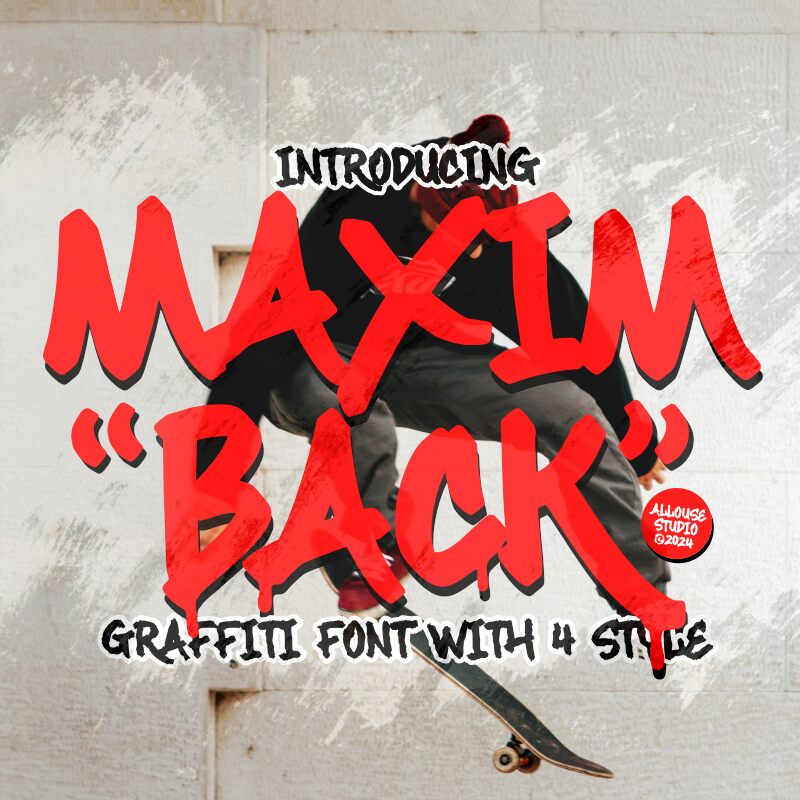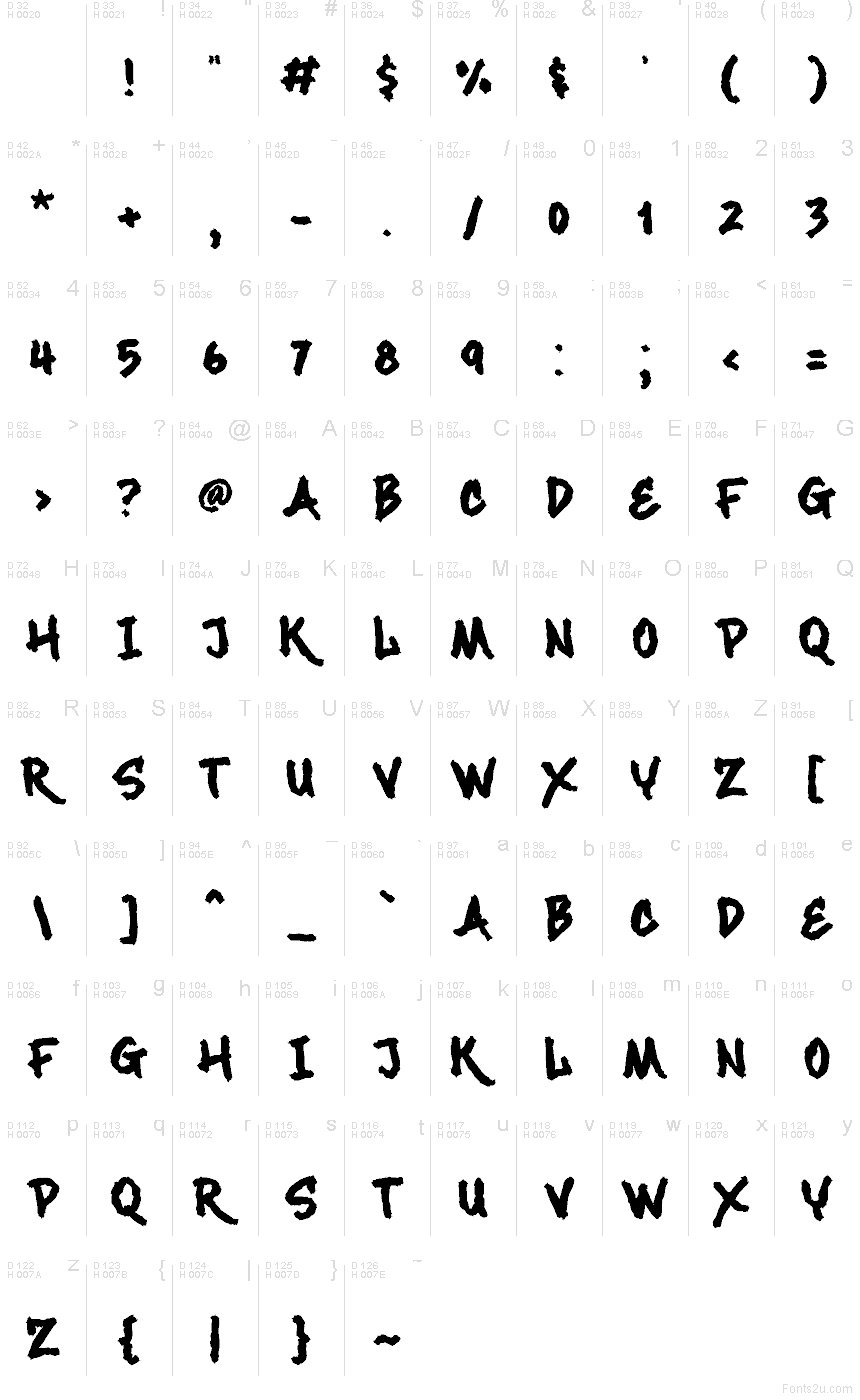
خط Maximback Distressed من Allouse.Studio هو خط مجاني بأسلوب الجرافيتي، يتميز بضربات قوية ومشبعة بالطلاء تبدو وكأنها رُسمت بسرعة على الجدار. تمنح الحواف الخشنة والنهايات الحادة الحروف ملمساً خاماً وجريئاً، مما يجعله يبدو أقرب إلى "تاغ" الشوارع اليدوي منه إلى خط الفرشاة المصقول.
هذا المظهر الخام مثالي لتصاميم ملابس الشارع (ستريت وير)، وملصقات الموسيقى، وعلامات التزلج التجارية، ونشرات الفعاليات، وعناوين التواصل الاجتماعي حيث تبدو الخطوط النظيفة مملة جداً. إنه خيار ممتاز للعناوين القصيرة والعبارات المؤثرة، خاصة عندما تريد أن تكون خشونة الفرشاة هي العنصر البصري الأساسي في التصميم.